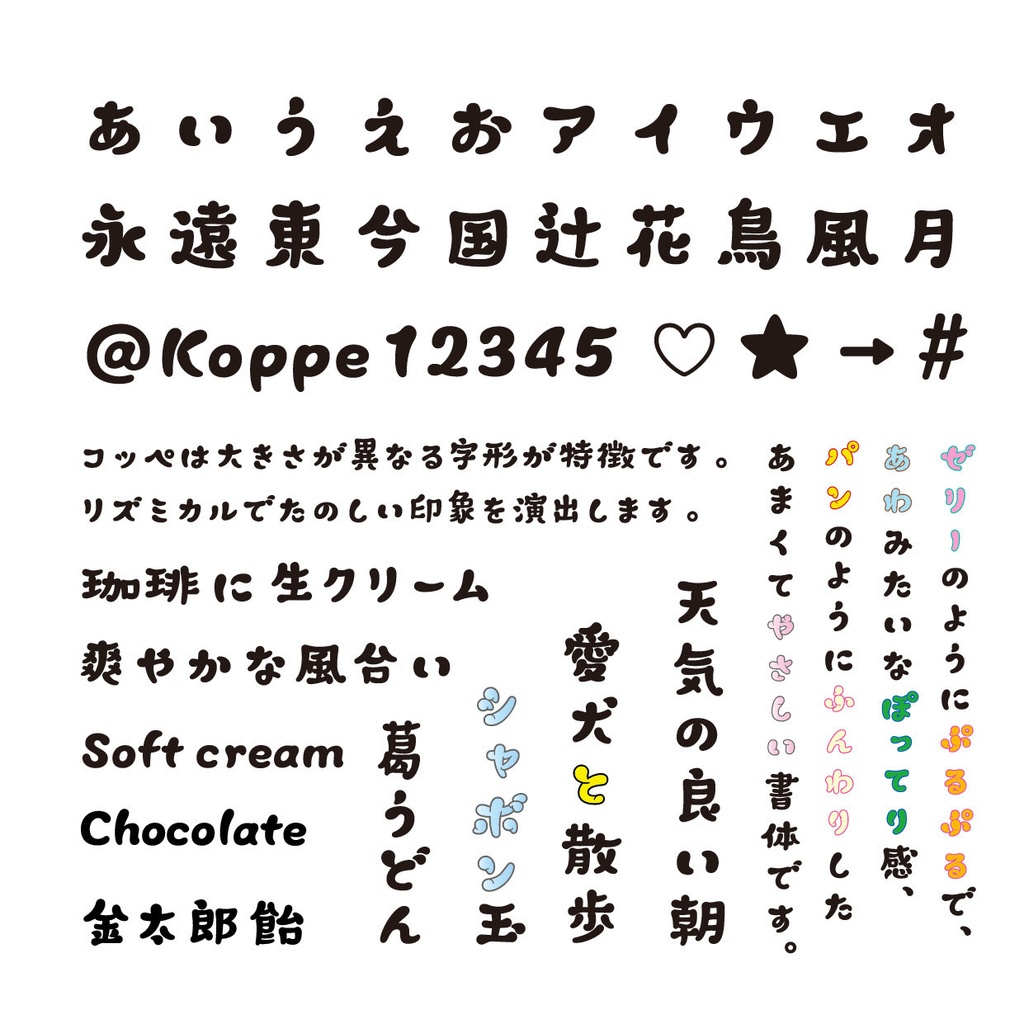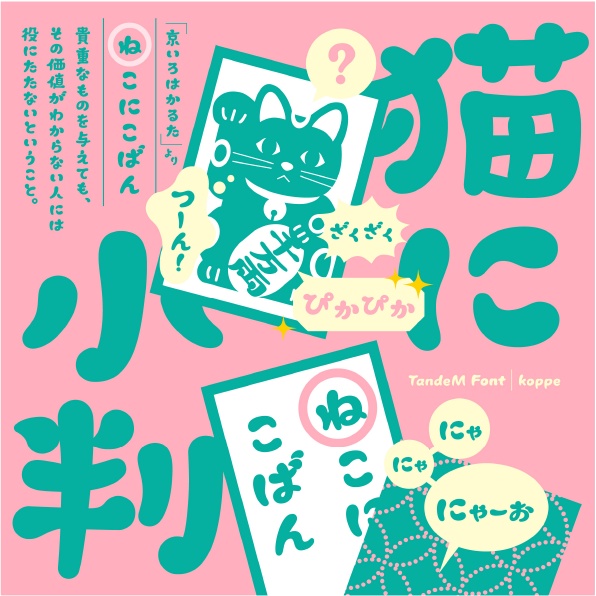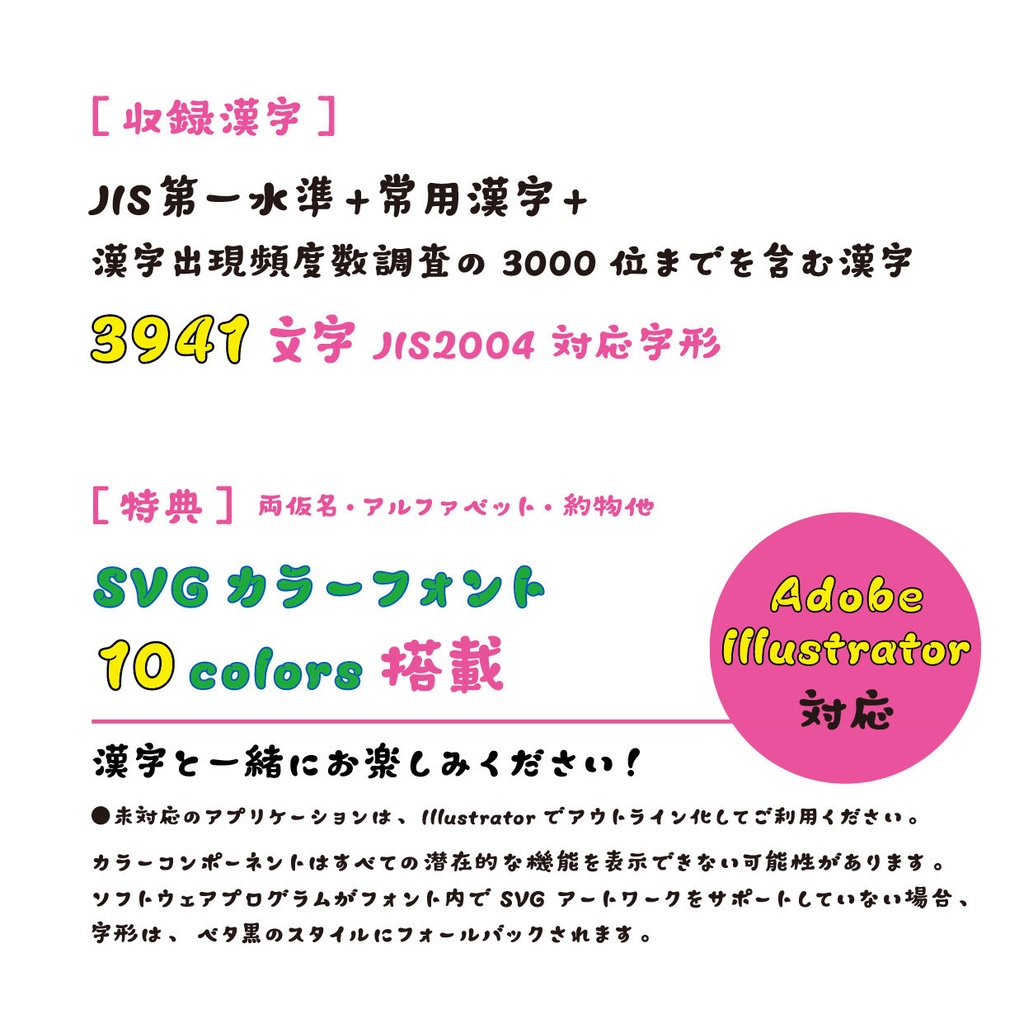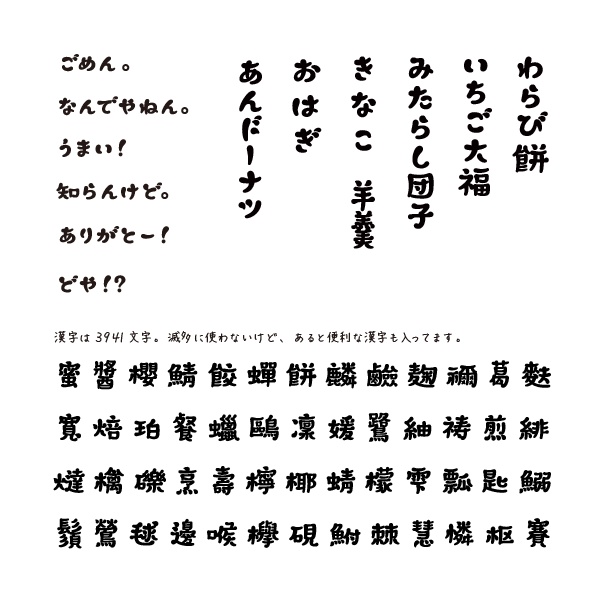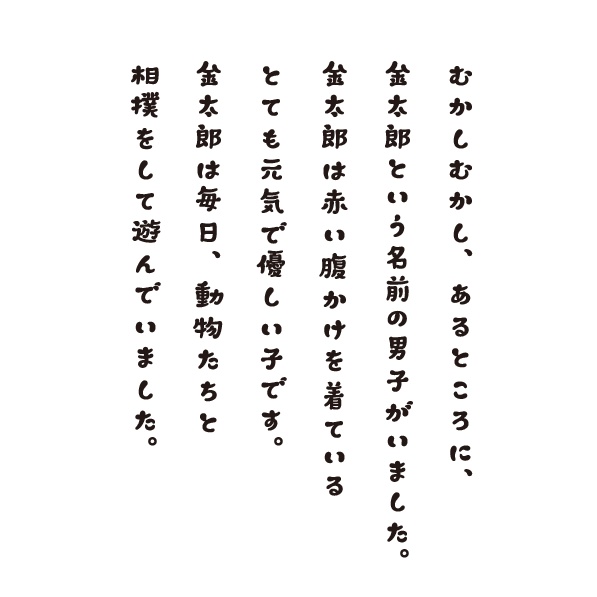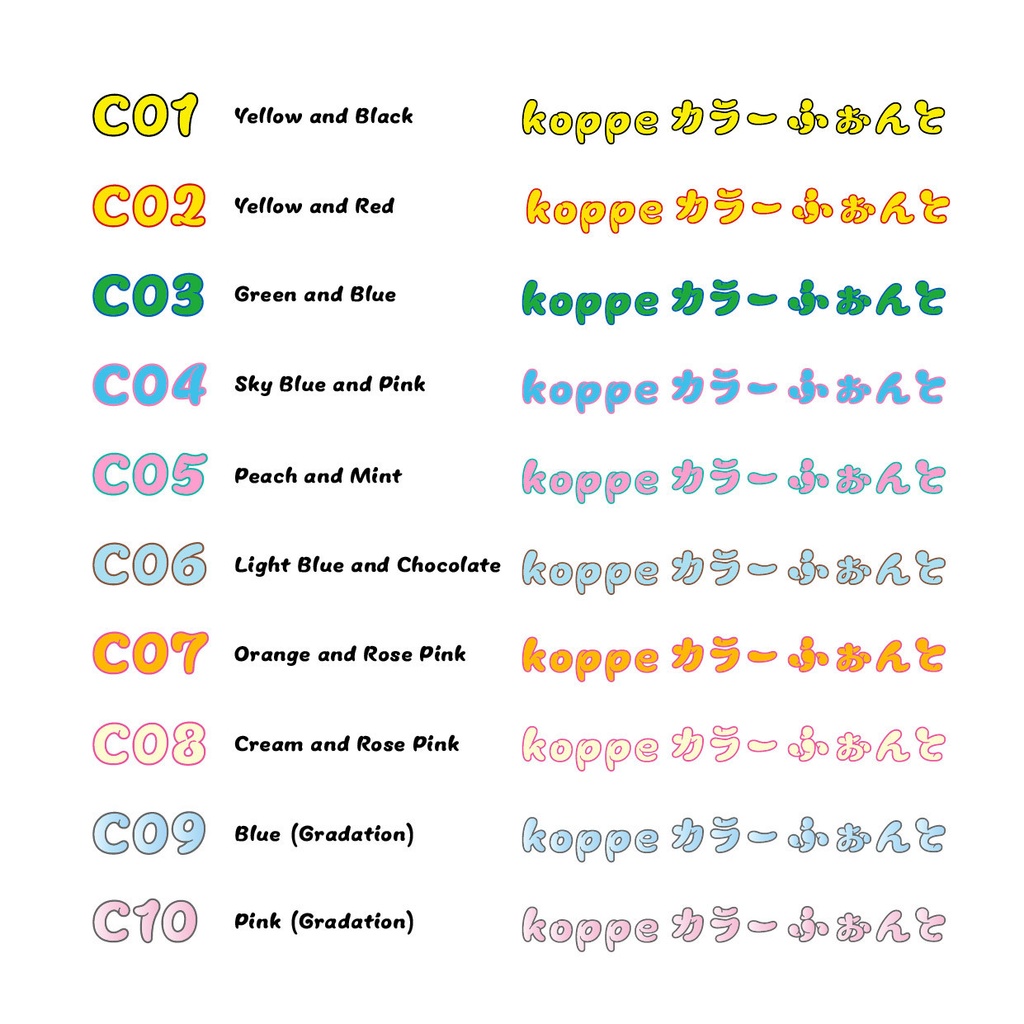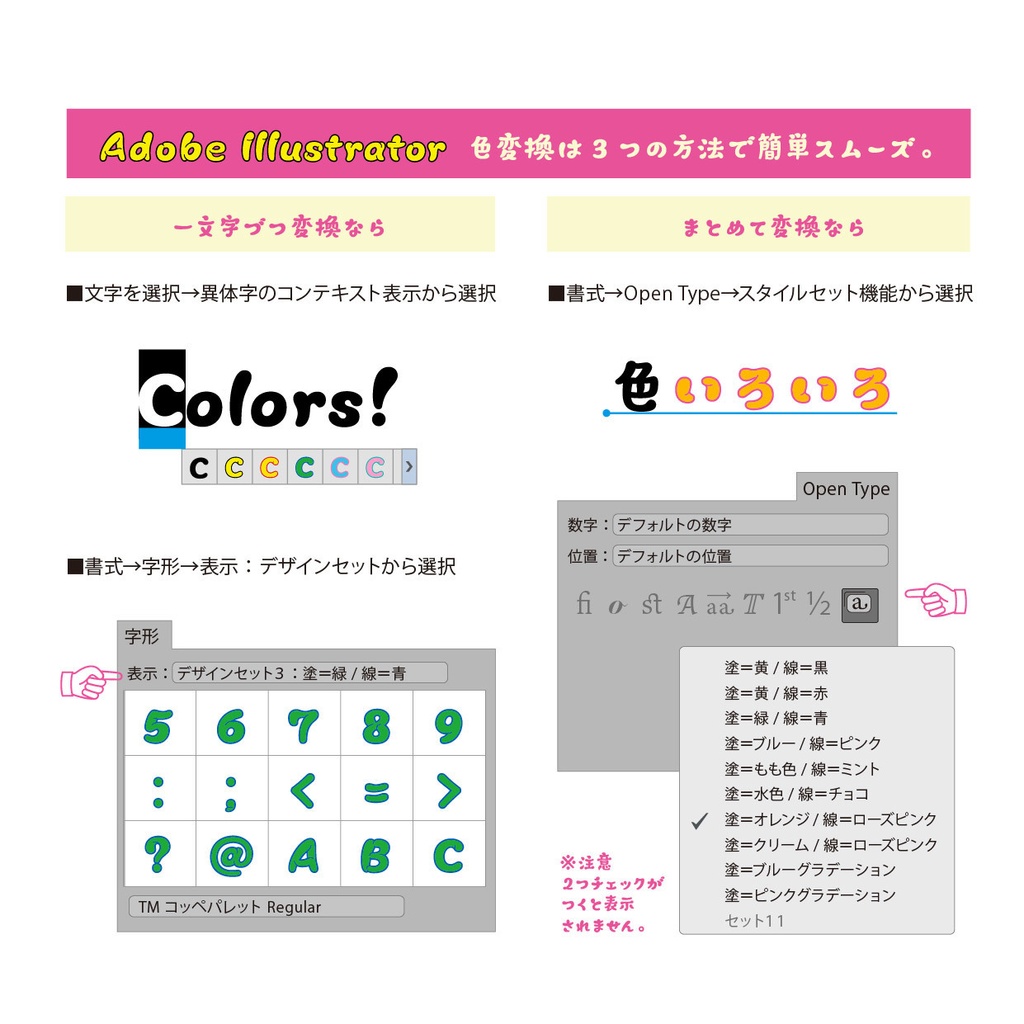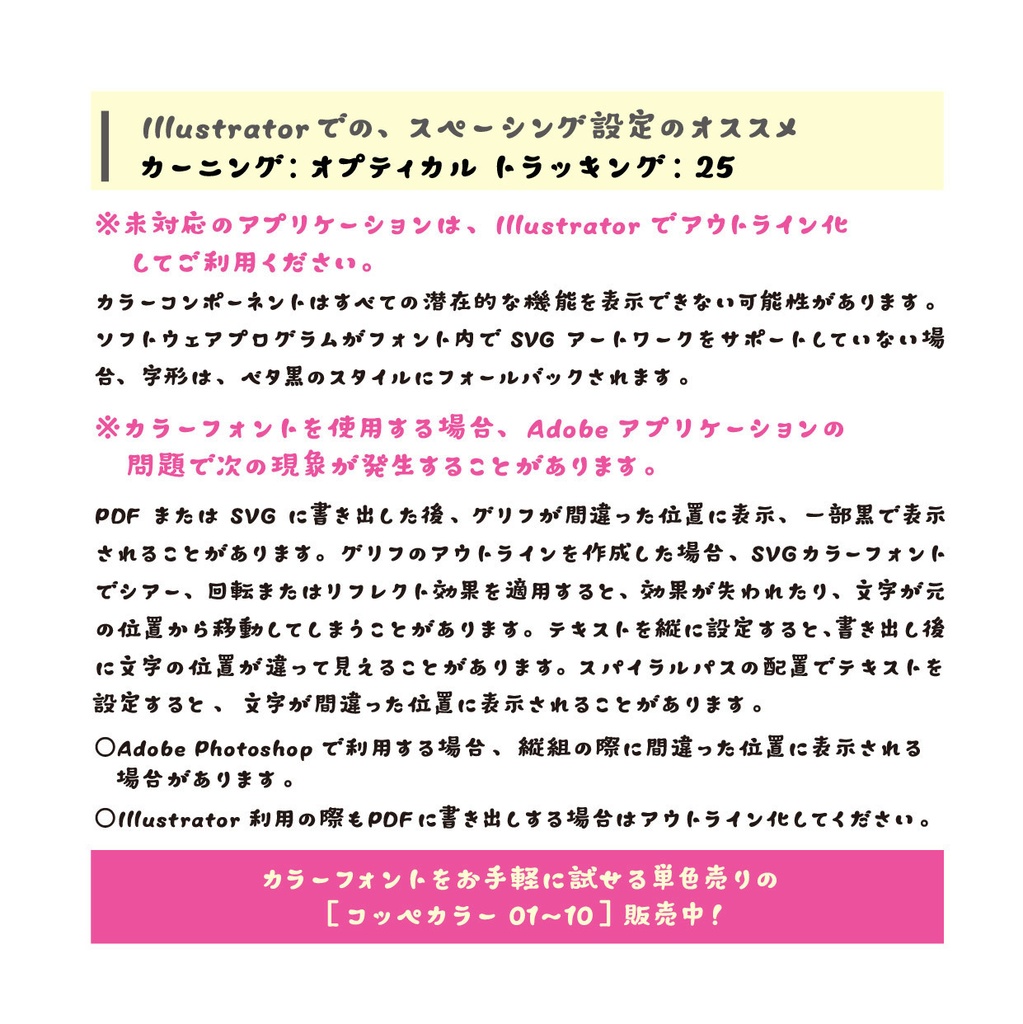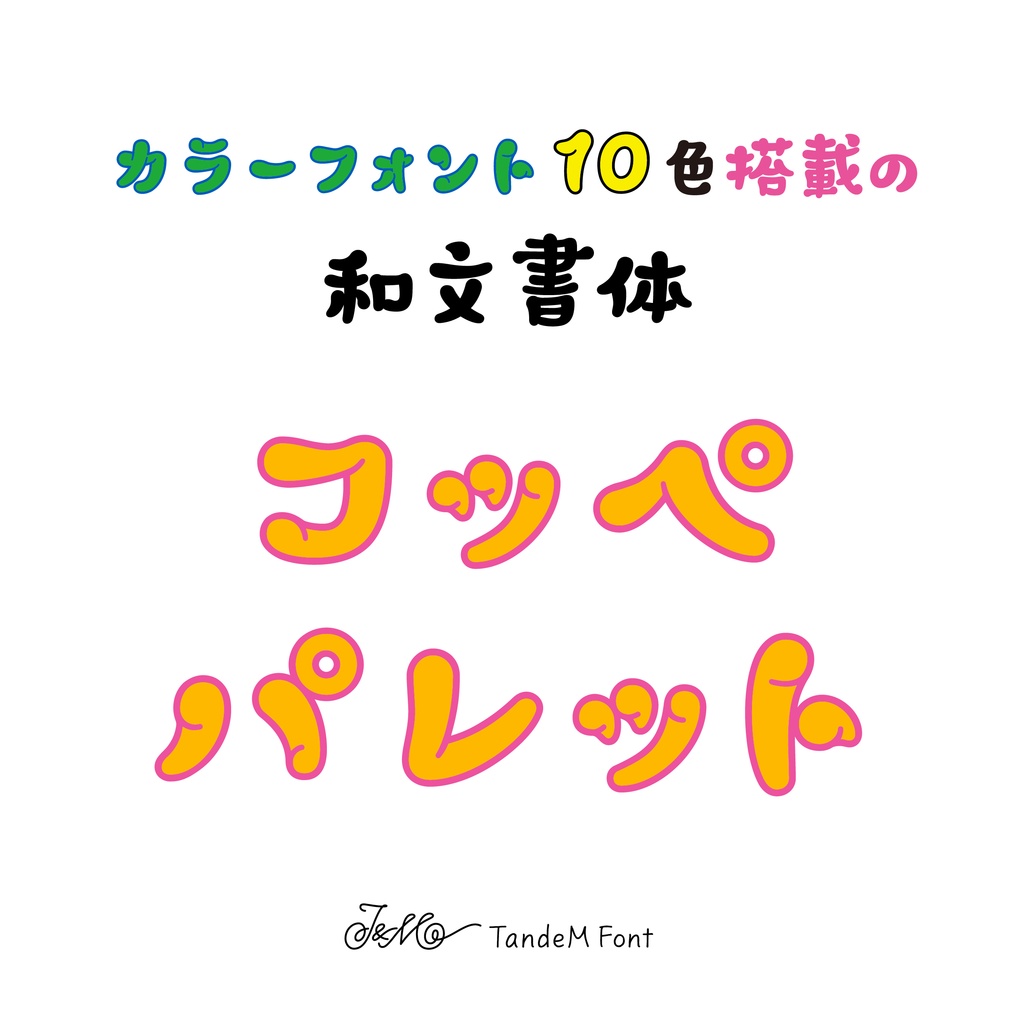
コッペパレット(特典:SVGカラーフォント搭載)
漢字とも組みやすく、自分で作るにはちょっと面倒な袋文字で「カラーフォント搭載の和文書体」を制作しました。 発展途上のカラーフォントは時折予知できない現象が発生することがあります。ご利用いただく際は下記の注意事項をご理解の上、ご自身の責任の範囲内でご利用いただければ幸いです。 カラーフォントを利用される方には Adobe Illustratorでの使用を推奨しています。 ■カラーコンポーネントはすべての潜在的な機能を表示できない可能性があります。ソフトウェアプログラムがフォント内で SVG アートワークをサポートしていない場合、字形は、ベタ黒のスタイルにフォールバックされます。 ■カラーフォントを使用する場合、Adobeアプリケーションの問題で次の現象が発生することがあります。 PDF または SVG に書き出した後、グリフが間違った位置に表示されることがあります。グリフのアウトラインを作成した場合、SVG カラーフォントでシアー、回転またはリフレクト効果を適用すると、効果が失われたり、文字が元の位置から移動してしまうことがあります。 テキストを縦に設定すると、書き出し後に文字の位置が違って見えることがあります。スパイラルパスの配置でテキストを設定すると、文字が間違った位置に表示されることがあります。 ○Adobe Photoshopで利用する場合、縦組の際に間違った位置に表示される場合があります。 ○Illustrator利用の際もPDFに書き出しする場合はアウトライン化してください。 詳しくはAdobe サポート:OpenType-SVGカラーフォントを参照ください。 https://helpx.adobe.com/jp/fonts/using/ot-svg-color-fonts.html 【動作環境】 OS X 10.9~10.11、macOS 10.1〜12.2 Windows8.1,10,11 【文字セット】JIS第一水準、常用漢字、文化庁漢字出現頻度数調査の3000位までを含む漢字3941文字(JIS2004対応字形)と、両かな、欧文、非漢字を含む、総文字数約4580字。特典としてSVGカラーフォント、両仮名、欧文、非漢字を含む452字 本フォントは下記の条項すべてにご同意いただける方にのみ、使用が許諾されます。プログラム及びデータファイルの権利・著作はタンデムが有しています。 □使用条件 お客様は本フォントを、お客様が所有する2台までのコンピュータにインストールして使用することができます。事業所など、複数人でご利用になる場合は必ず1台ごとにライセンスをご購入ください。無断コピー、サーバー及びフォントストレージ等での共用、またリース、転売、頒布などはいずれも著作侵害となります。 お客様は、自らの責任において本フォントを利用するものとします。 当社はお客様の利用に際して、技術的なサポートは行いません。 □禁止事項 以下のご利用条件では使用することができません。 ①本フォントの一部または全部を第三者に譲渡または貸与すること。 ②本フォントを元にして類似または同一フォントを作成すること。 ③本フォントを使用して商標を作成すること ④画像編集、動画編集を目的とするソフト・アプリへの本フォントの埋め込み(必要な場合は別途ご相談ください) ⑤本フォントをフォントファイルのサーバーへアップロードすること ⑥本フォントで対価を得る目的での二次使用 □保証・免責 ①本フォントに誤字などの瑕疵が発見された場合は修正します。 中には風合いを優先した字形があります。ご確認の上ご利用ください。 ②当社は、本フォントのご使用により生じたいかなる損害についても、 これを賠償する責任を負いません。 なお、お客様が本契約に違反した場合には、当社は本契約を取り消すことができます。 本契約が取り消された場合でも、当社はお客様に対して一切の返金等を行いません。 □使用許諾範囲 印刷:出版、広告、販促物、製品への使用 文字の加工(ロゴ):加工、変形、分解など ※商標権などの無体財産権を取得する場合は、別途二次使用権契約とライセンスが必要になります。 Web:画像としての表示 ※フォントファイルのサーバーへのアップロードは不可。 デジタルコンテンツ・電子書籍:画像としての表示 ※表示機器へのフルセットフォントの組み込みは不可、別途二次使用権契約とライセンスが必要です。 ゲーム・アプリ:画像としての表示 ※対価を得る目的での使用は、別途二次使用権契約とライセンスが必要です。 映像・放送:映画、放送番組、CF、DVD ※YouTube用の動画や動画広告、プロモーション用動画での使用は一次使用権の範囲内でご使用いただけます。 追加許諾: 本製品では、フォントをWindowsやMacにインストールして使用する通常の方法だけでなく、Canvaなどのオンラインサービス上にフォントファイルをアップロードして使用する方法も許諾しています。 ただし1ライセンスにつき、1名・2デバイスまでの使用に限りますのでご注意ください。PC、タブレット、スマートフォンなど複数人・複数台で使用される場合は、必要となる台数分のライセンス数をご購入ください。 また、不特定多数の方が使用するデバイスでの使用に関しては、別途二次使用権契約とライセンス料が必要となります。ご不明な場合はお問い合わせください。